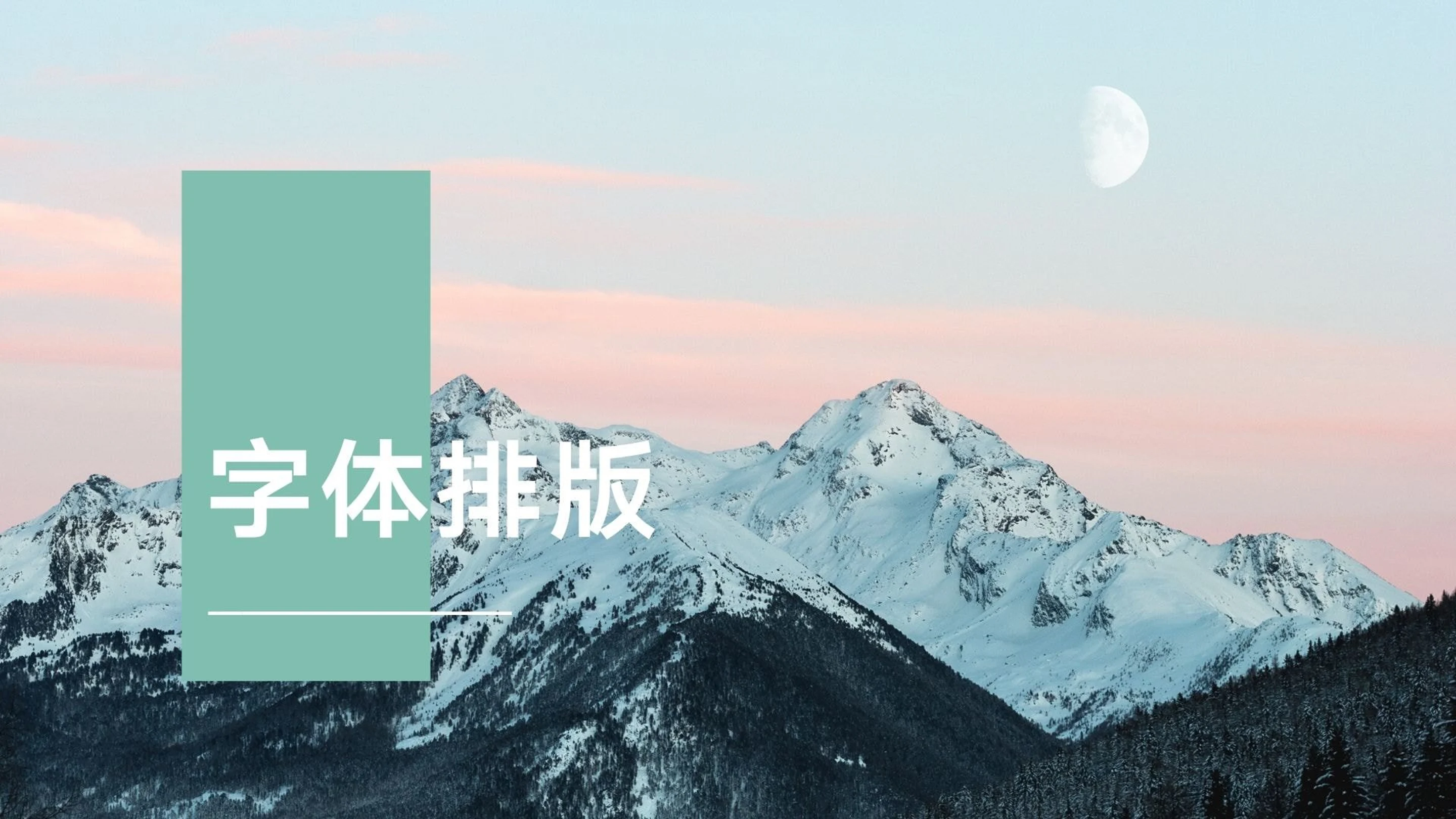
字体排版,如何更有设计感
想要把我们的中文字体排印做到更有设计感,首先需要明确什么样的效果是你想要的。是能准确表明设计主题?还是淋漓尽致展现中文的风骨?或是能够展现独属于中文细腻大气的美感?
也许,你也没有摸清自己想要表达的含义,下面的这些建议也许能够帮到你!
1.选择优质字体
什么是字体?在一定程度上,字体是可以被定义为文字的外在形式特征。也就是文字的风格,是文字的外衣。 优质字体是如何定义的?其实严格看来只要字体使用恰当,就没有优质与劣质之分。
每种字体,都有着不同的性格,设计师要根据场景来对他们进行使用或者搭配。
想要在平面排版时突出中文的美感,最重要的是你要完全理解设计场景,然后选择字体进行搭配。
比如颜楷+宋体就很适合传统风格的设计。
瑞意宋+黑体就会让设计整体增加时尚感。
2.善用竖排版
中文可以有竖排版,并且对读者对竖排版接受度高,这得益于我们古代的书写印刷习惯,大多以竖排版为主,这也让当代竖排版模式看起来更有东方味道。
中文字体的方块结构,在竖排版的方式下将美感再次展现。竖排版的阅读和印刷传统,也更符合中文字体的东方味道。善用竖版排版,当你想做一个富含东方韵味的设计时可以达到事半功倍的效果。
3.善用汉字的大小对比
一级字体在达到吸引注意的目的后,二级字体也要进行相应配合。
下图的重阳海报⁠(在新标签页或窗口中打开)就是一个很好的文字搭配,在一级标题手写体作为重点进行凸显的时候,二级及以下标题就可以使用识别度较高的字体比如黑体,宋体。在这里注意的是,二级标题尽量不要使用手写字体,因为会让人忽视你想在二级标题中凸显的重点。
4. 利用简单图形为文字版式作辅助
中文文字更加注重装饰性,甚至文字可以作为画面的主题,因为文字的图形化强。
以下图的海报为例,图中的文字就不单单只是文案这一个功能,文字衔接处的鹊桥处理,就点名了主题。在这个海报中,文字就成为了画面的主题。
中文字体难在没有定式,也美在没有定式,文字可扩展性强。你完全可以在现有的文字上进行再次创作和发挥。
文字本身没有定式,这也给人很多创作的空间。同样的文字,你用不同的创作方式做出来的就是不一样的效果。参考下图范例。文字的拆解与组合,将海报的主题进行了再次地确立。
5.调节字间距与行间距是设计的好习惯
前面说了那么多专业的步骤,这里我们就交代一点基础工程!那就是调整好字间距和行间距!
不要小看他们两个,正是它们两个才是排版设计的基础关键!
字间距影响了一行或者一个段落的文字的密度。
行间距则是影响着每行之间的密度。
间距小了,难免会出现紧凑喘不过来气的窒息感。
间距大了,则会出现空旷无关键点的尴尬。
所以想要达到字体排版的高格调,请答应Canva酱调整好字间距和行间距好吗!
其实中文字体排印并不难,只要结合具体场景遵循好基本排版理念,你也可以排出自己满意的格式~